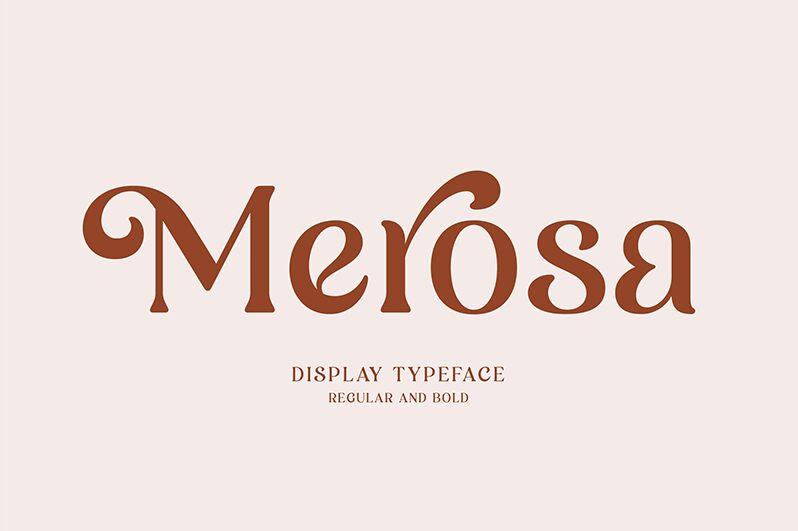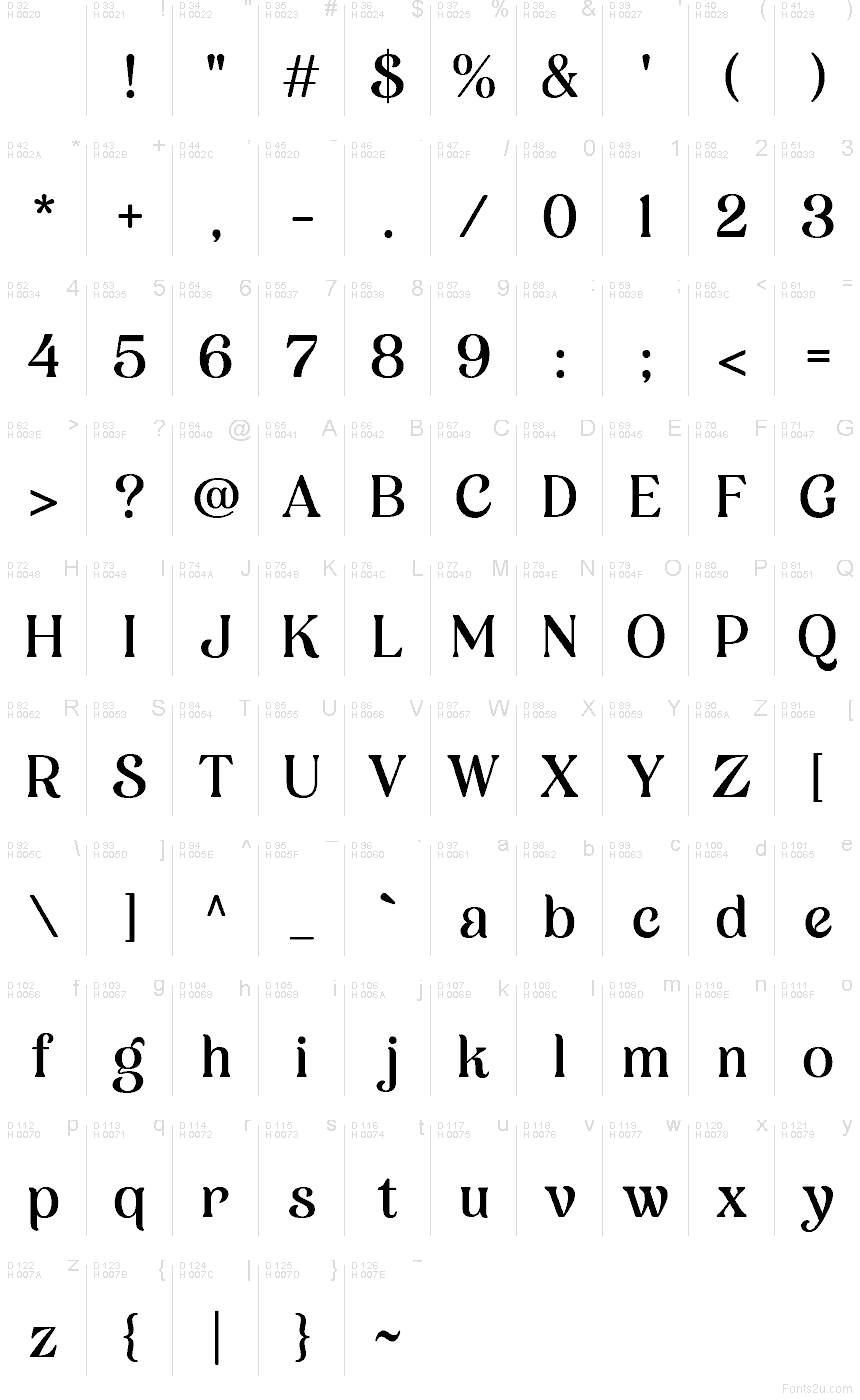
Diseñada por Akhmad Reza Fauzi, Merosa es una tipografía con remates de estilo retro, gratuita, con proporciones teatrales y contrastes pronunciados en el grosor del trazo. Sus amplias mayúsculas presentan remates puntiagudos y acampanados, mientras que las minúsculas, más esbeltas, conservan ese mismo acabado nítido. Las letras redondeadas son amplias y de trazo fluido, lo que le otorga a la fuente una reinterpretación sofisticada y orientada a la moda de la rotulación vintage para titulares.
Una firma de moda exclusiva o una marca de perfumes con arraigo tradicional podrían utilizarla para evocar lujo con un toque sutilmente excéntrico. Sus curvas llamativas también se adaptan a portadas de revistas, carteles de eventos y empaques de alimentos de alta gama, donde la tipografía puede transformarse en un emblema ilustrado o en un rótulo decorativo, más allá de un simple nombre de producto.